【無料】おしゃれな日本語フォント8選とおすすめアプリ TOP3【2025年最新版】
Instagram や Twitter に投稿されているおしゃれな写真には良くかわいいフォントが使われていますよね。
文字フォントは写真の次に眼に入ってくる情報ですので、画像共有においては非常に重要な役割を果たします。
せっかくエモい写真を撮ったのに、それに付けるフォントが明朝体では雰囲気が崩れてしまいます。
そこで、今回はおしゃれな日本語フォントのおすすめ 8 選と、それら全てを使えるアプリについてご紹介していきます。
みんなが使っているおしゃれなフォントについて詳しくなって、素敵な投稿を作ってくださいね。
おしゃれなフォントって?
「フォント」とは文字の字体、スタイルの事を指します。
たかが文字の字体と思われがちですがフォントは意外と重要な役割を担っていて、フォントによって、作品全体のイメージやその文章を読む人の印象にまで影響します。
ですので、ご自身の SNS 投稿や YouTube のサムネイルが「なんか固い」とか、「どうしても古臭いイメージ」などでお悩みの方は、フォントを変えてみることをおすすめします。
フォントには沢山の種類があって、公官庁などのお堅いイメージの「明朝体」や「Century」、幼稚園のお知らせや小学校などでよく見かける少しくだけたイメージの「メイリオ」、強調したい時や雰囲気を柔らかくしたい時に使う「にくまる」など、外国語も含めるとそれこそ数千を超えるフォントが存在します。
特に日本には漢字・ひらがな・カタカナが存在し、色々な表現ができるのでフォントも多種多様です。
次項ではそんな多種多様にあるフォントの中から、おすすめのフォント8選について解説します。
ぜひ、フォントに詳しくなって、実際に使ってみてくださいね。
みんなが使っているおしゃれなフォント8選!
① ラノベ POP
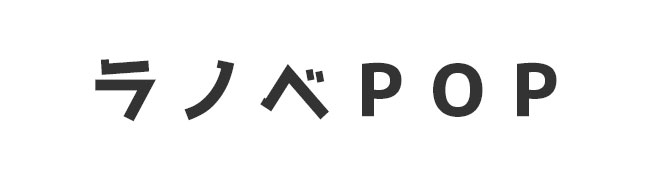
ラノベ POP は、太めのペンで丁寧に書いたような可愛らしい太字フォントです。インパクトがあるうえに読みやすいので、YouTubeのサムネやポスターなどによく使われています。
② うつくし明朝体
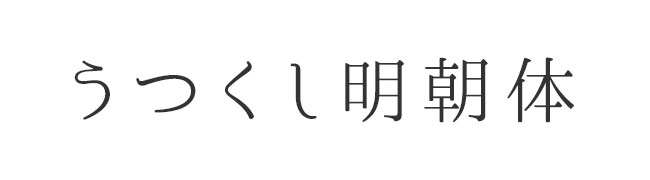
うつくし明朝体は、数ある明朝体の中でも人気の高いフォントです。文字の美しさが特徴で、読む人の読みやすさを意識したフォントと言えます。
大人っぽい雰囲気を出したい時などによく使われます。
③ バナナスリップ
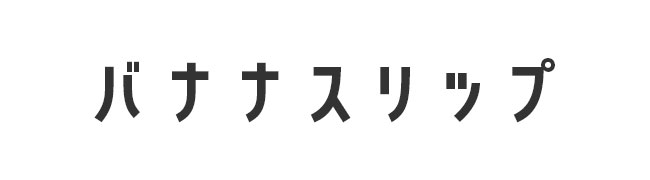
バナナスリップは、文字の幅が細く丸っこいフォントです。可愛らしいので、読みやすさとインパクトを両立させつつインパクトが欲しいときなどに使いやすいフォントと言えます。YouTube のサムネイルや動画内のテロップやテキストによく使われています。
④ にくまるフォント
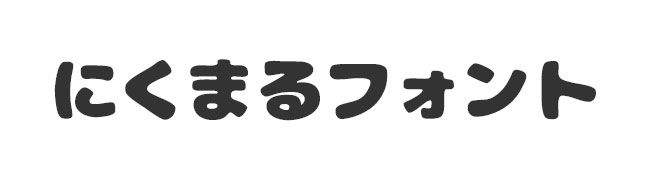
にくまるフォントは、まるっとした文字でやわらかなフォントです。可愛い見た目は女性が好きなため女性向けの動画や SNS 投稿に使いやすいでしょう。文字が太く読みやすいので注目して欲しい所などにスポットの様に使ったり、見る人の印象に残したいキャッチコピーなどによく使われます。
⑤ あんずもじ
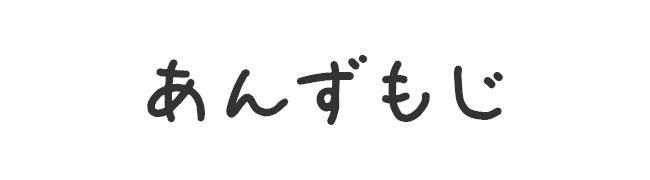
あんず文字は、女性の手書き風なフォントです。手書き風フォントの中では全体的に統一感があるフォントですので使いやすく、硬い雰囲気を出したくない時などに使うと良いでしょう。YouTube のサムネイルや SNS で日記や日常の様子を投稿する時などに使われます。
⑥ コーポレート
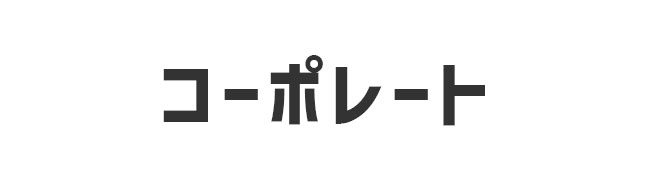
コーポレートはシンプルながら少し縦長のデザインで、普通のフォントより目立つ上に読みやすいので、商品の商会や催し物のポスターなどに使うと良いでしょう。その読みやすさと少し硬い雰囲気から、宣伝・広告、YouTube のサムネなどによく使われます。
⑦ やさしさゴシックボールド
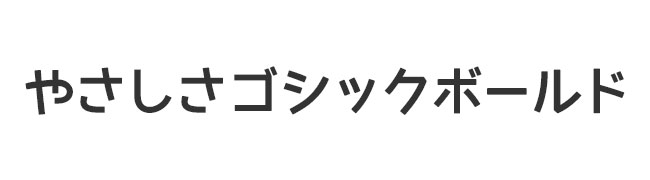
やさしさゴシックボールドは、手描き風の柔和な雰囲気が特徴のフォントです。太めのゴシックですので、硬くなり過ぎず、かと言って崩しすぎない丁度いい軽いイメージですので、色々な画像に使うことが出来るでしょう。文字が太いので YouTube のサムネなどで使う人が多いです。
⑧ 851 ゴチカクット
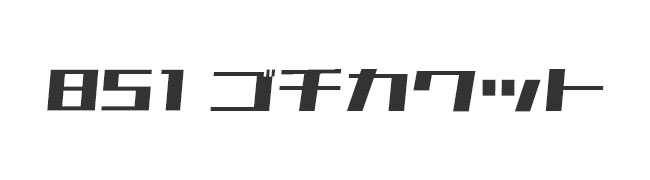
851 ゴチカクットは、カクカクしたイメージのフォントです。文字の縦が太く、横が細いインパクトのあるフォントで、少ない文字数で印象的に使うのがおすすめです。YouTube のサムネで使っている人を多く見かけますが、使い道は少し難しいかもしれません。
今回は、このテンプレートを使ってみます。
ステップ 2:フォントを変更してみましょう
さっそくテンプレート内テキストのフォントを変更してみましょう。
やり方は簡単です。
フォントを変更したいテキストをタップして選択状態にします。その後画面下部にあるメニューから「フォント」をタップしてみてください。
すると、様々なフォントを選ぶ画面になりますので、その中から使ってみたいフォントを選んでタップして適用するだけです。
今回は「ほっこり」というテキストを「にくまるフォント」に変更してみました。
ついでに「秋の箱根旅」というテキストのフォントもそれらしく変更してみましょう。
先程と同様に「秋の箱根旅」部分をタップ選択状態にして、「フォント」をタップしてフォント選択画面にします。
このテキストには「解星 デコール」というフォントを使用してみます。
さて、フォントを変更する前と、変更後の画像を並べてみました。
いかがですか?かなり印象が変わったと思います。
このように、フォントは使い方次第で画像のイメージや雰囲気を変えることができます。
Premeoの豊富な日本語フォントを使いこなして、あなたの写真をさらに魅力的にしてみてくださいね。
Promeo で使えるテンプレートに様々なフォントに変更した画像を作ってみました。
どのフォントもおしゃれでかわいいですよね。
是非デザインの参考にしてみてください♪
Promeo はインストール無料なのに豊富な日本語フォントを使えますので、色々なフォントを使ってみたい人に非常におすすめです。
もちろんフォントを使うだけではなく、動画や SNS 用画像のプロ級加工もできますので、興味のある方はぜひ試してみてくださいね。